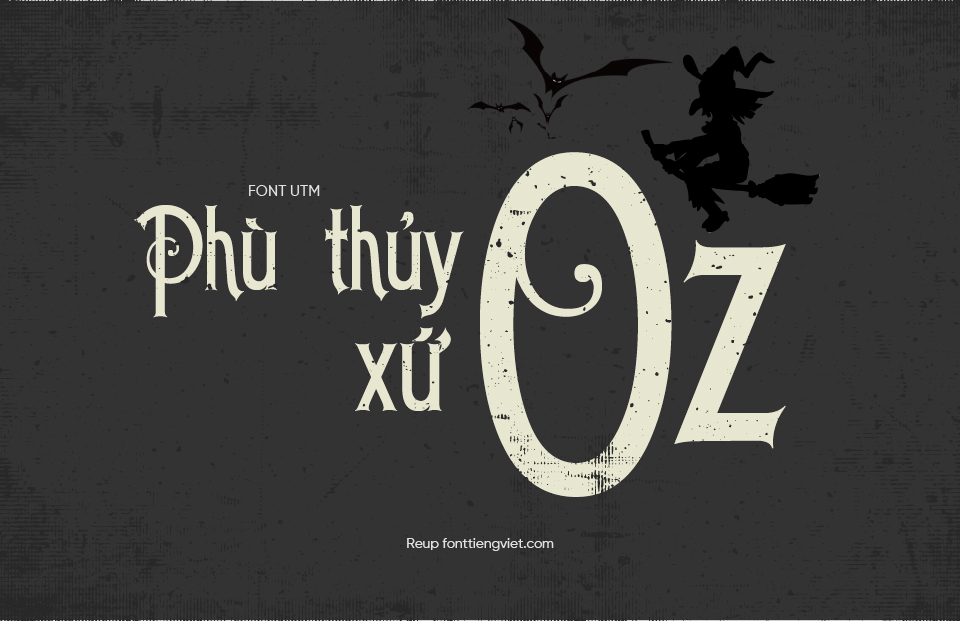
Font việt hóa UTM Billhead 1910
Tải Font việt hóa UTM Billhead 1910 – Phong cách cổ điển tinh tế
Giới thiệu về Font việt hóa UTM Billhead 1910
Trong thế giới đồ họa hiện đại, việc tìm kiếm một bộ Font Miễn Phí mang đậm hơi thở lịch sử nhưng vẫn đảm bảo tính thẩm mỹ cao luôn là ưu tiên của các nhà thiết kế. Font việt hóa UTM Billhead 1910 chính là giải pháp hoàn hảo cho những ai yêu thích phong cách Retro và Vintage. Đây là bộ font được lấy cảm hứng từ các bảng hiệu và hóa đơn cũ vào đầu thế kỷ 20, giúp mang lại vẻ đẹp hoài cổ, sang trọng cho mọi dự án thiết kế.
Đặc điểm nổi bật của font chữ
Bộ Font việt hóa UTM Billhead 1910 sở hữu những đường nét mạnh mẽ, dứt khoát nhưng không kém phần uyển chuyển. Đặc biệt, phiên bản việt hóa giúp người dùng dễ dàng sử dụng trong các phần mềm thiết kế phổ biến mà không lo lỗi hiển thị dấu tiếng Việt. Sự cân bằng giữa các khoảng cách chữ giúp mẫu font này trở nên dễ đọc và bắt mắt trên các ấn phẩm in ấn như bìa sách, thực đơn hay nhãn hàng hóa.
Ứng dụng thực tế của Font việt hóa UTM Billhead 1910
Nhờ vẻ ngoài đặc trưng, bộ font này thường được ưu tiên sử dụng trong thiết kế logo, poster phim tư liệu hoặc tiêu đề bài viết cần sự trang trọng. Các bạn học sinh và giáo viên cũng có thể áp dụng font chữ này vào các bài thuyết trình về lịch sử hoặc văn hóa để tăng thêm tính thuyết phục và sinh động cho nội dung.
Lưu ý khi sử dụng font
Để phát huy tối đa vẻ đẹp của font chữ này, bạn nên kết hợp với những tông màu trầm hoặc hiệu ứng giấy cũ. Việc sử dụng đúng ngữ cảnh sẽ giúp thông điệp của bạn trở nên sâu sắc và có hồn hơn bao giờ hết.
Kết luận về bộ font cổ điển